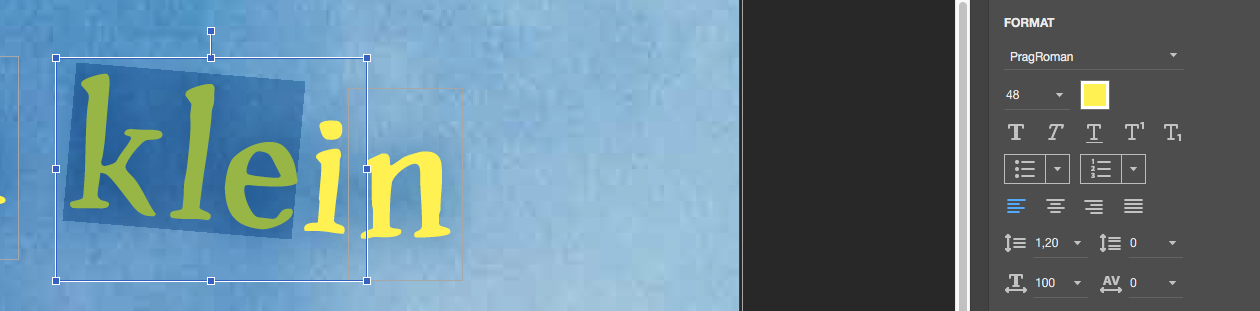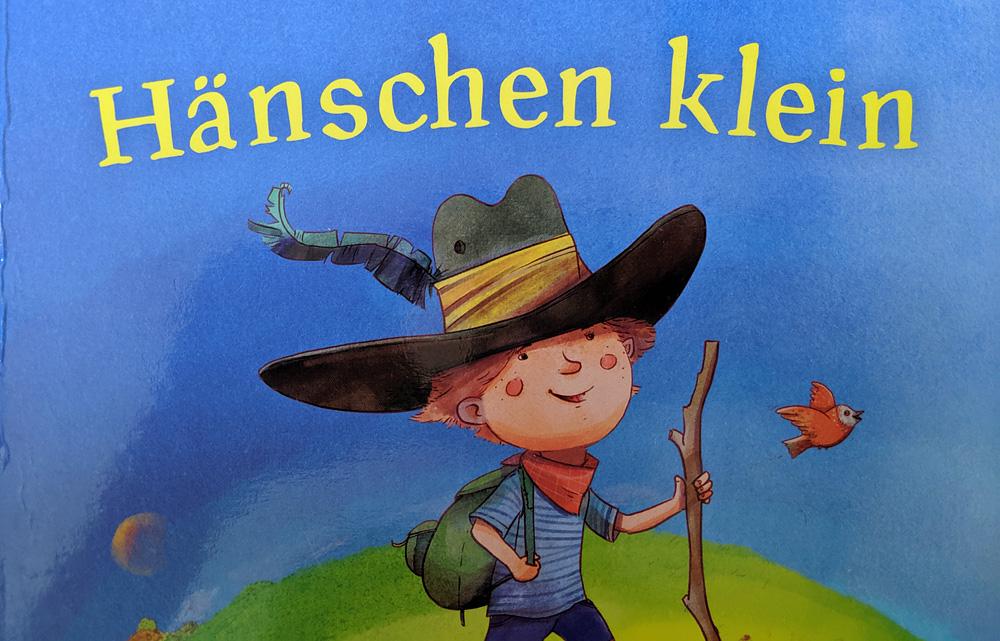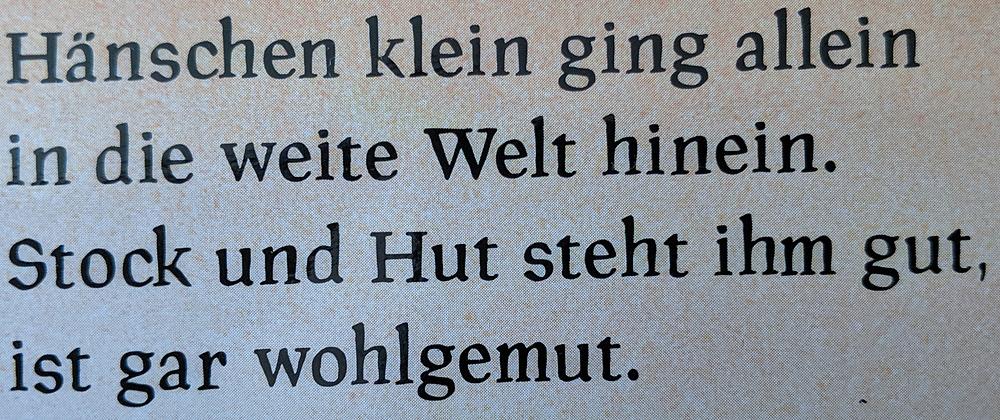
Antiqua-Schrift von Hänschen klein
Suche die Antiqua aus dem Buch Hänschen klein vom Eulenspiegel Verlag. (wurde auch in Hänsel und Gretel verwendet) Mein erster Gedanke war irgendwas von Oldřich Menhart, was nach kurzer Recherche auch stimmte. Jedoch ist es nicht die Manuskript Antiqua von Profonts/++URW. Die verwendete Schrift wirkt noch etwas weicher. Das ä ist anders oder sind die restlichen Abweichungen eher druckbedingt?
Kennt Ihr noch andere Digitalisierungen?
edit: es ist sicher eine andere Digitalisierung. Die Unterschiede sind zu groß.
"PragRoman" heißt sie, verrät ein Blick in das pdf "Blick ins Buch" aus deinem link.